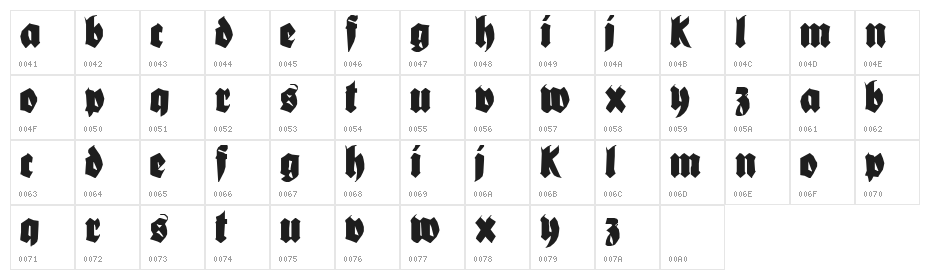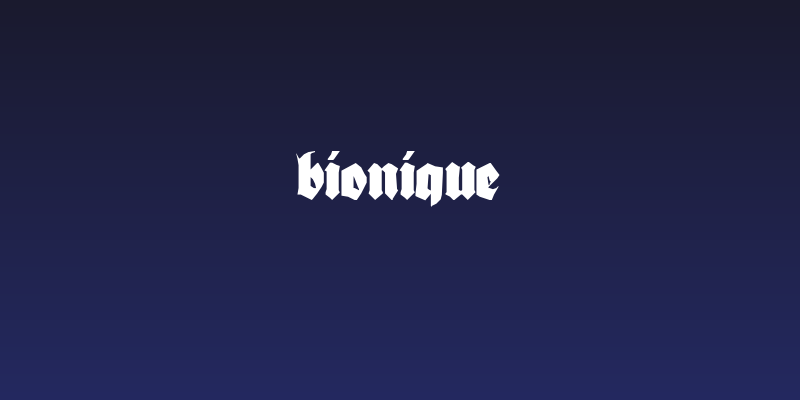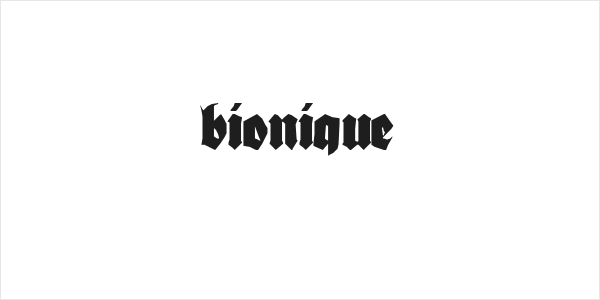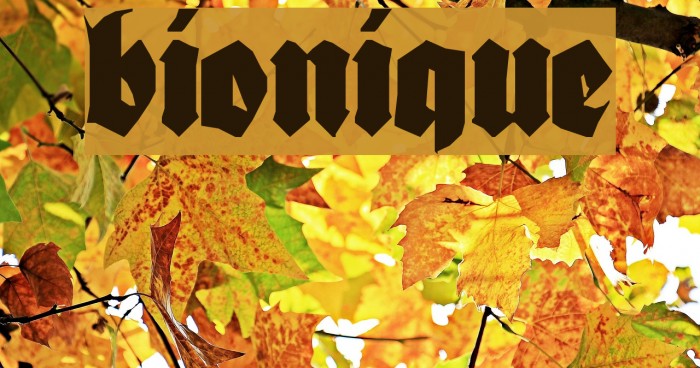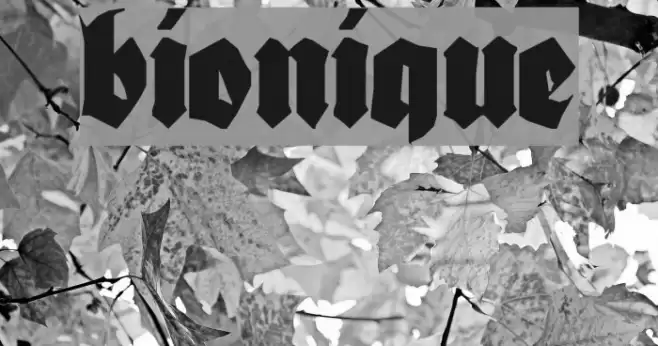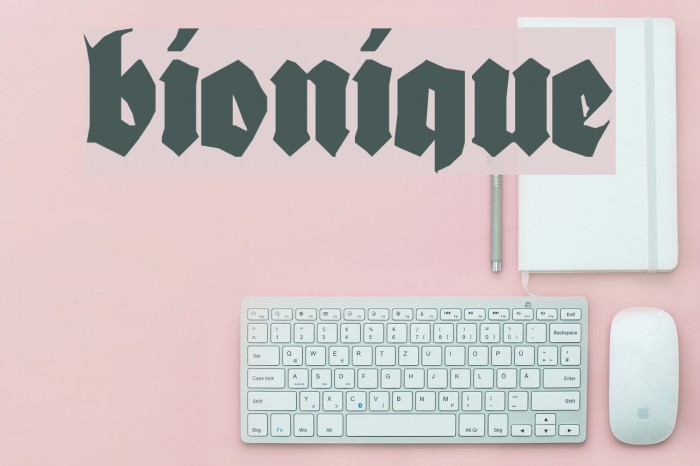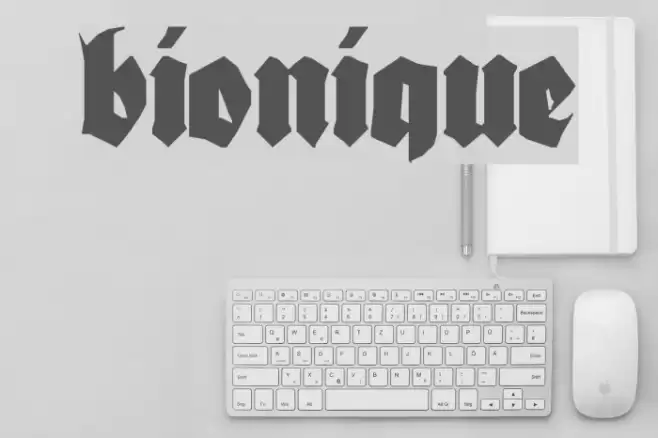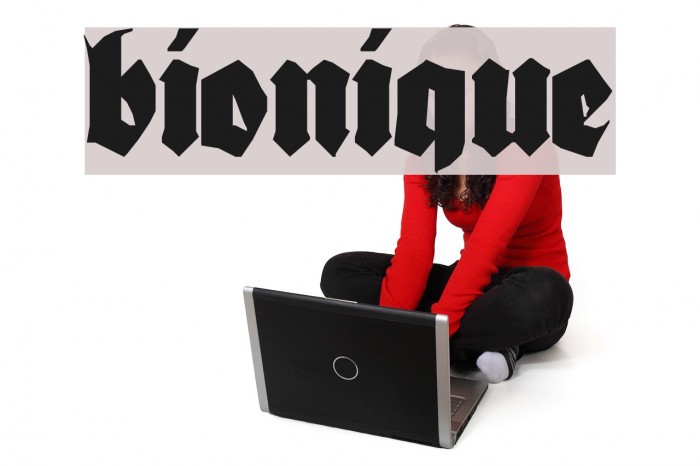
Bionique Font
✎ Gothic
| Categorii | Gothic |
| Caz de utilizare | Logos, Headlines, Decorative text |
| Proiecte propuse | Ideal for use in certificates, invitations, branding for luxury products, or any project seeking a historical or formal aesthetic. |